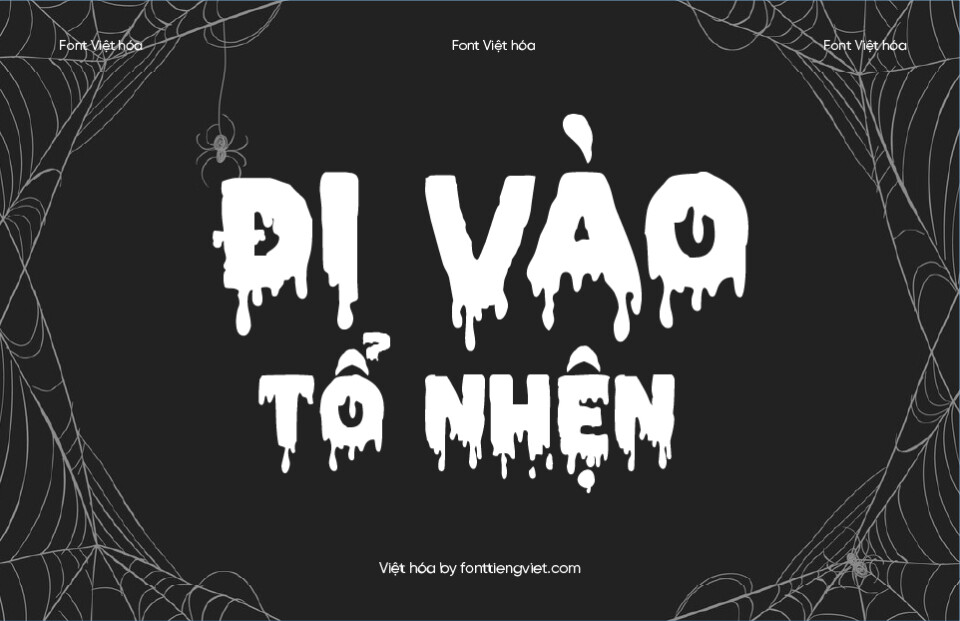
Font Việt hóa 1FTV VIP Pieces NFI – Font Halloween
Font Việt hóa 1FTV VIP Pieces NFI – Font Halloween – Đỉnh cao sáng tạo cho mùa lễ hội kỳ bí
Giới thiệu về Font Việt hóa 1FTV VIP Pieces NFI – Font Halloween
Mùa lễ hội hóa trang đang đến gần và việc tìm kiếm một bộ Font Miễn Phí ấn tượng là ưu tiên hàng đầu của các nhà thiết kế. Font Việt hóa 1FTV VIP Pieces NFI – Font Halloween chính là giải pháp hoàn hảo để mang lại không khí rùng rợn, ma mị nhưng không kém phần nghệ thuật cho các ấn phẩm của bạn. Bộ phông chữ này được đội ngũ 1FTV chăm chút kỹ lưỡng, đảm bảo hiển thị tiếng Việt mượt mà, không lỗi dấu, giúp các bạn học sinh và giáo viên dễ dàng thực hiện các dự án trang trí trường lớp hay làm thiệp mời sự kiện.
Đặc điểm nổi bật của Font Việt hóa 1FTV VIP Pieces NFI – Font Halloween
Phong cách thiết kế độc đáo và rùng rợn
Được lấy cảm hứng từ những mảnh ghép vụn vỡ và phong cách kinh dị cổ điển, Font Việt hóa 1FTV VIP Pieces NFI – Font Halloween sở hữu các đường nét thô ráp, góc cạnh đầy kịch tính. Mỗi ký tự giống như một tác phẩm nghệ thuật riêng biệt, tạo nên cảm giác huyền bí ngay từ cái nhìn đầu tiên. Đây là lựa chọn tuyệt vời cho các tiêu đề lớn trên poster, bìa sách hoặc các slide thuyết trình chủ đề kinh dị.
Tính ứng dụng cao trong giáo dục và thiết kế
Dù mang hơi hướng Halloween, bộ phông chữ này vẫn đảm bảo tính dễ đọc và tương thích tốt trên nhiều phần mềm đồ họa hiện nay. Người dùng có thể sử dụng cho các video ngắn, banner mạng xã hội hoặc thiết kế áo thun đồng phục. Việc sử dụng đúng phông chữ không chỉ giúp nội dung nổi bật mà còn truyền tải trọn vẹn tinh thần sáng tạo và sự đầu tư nghiêm túc của người làm nội dung.
Kết luận và trải nghiệm Font Việt hóa 1FTV VIP Pieces NFI – Font Halloween